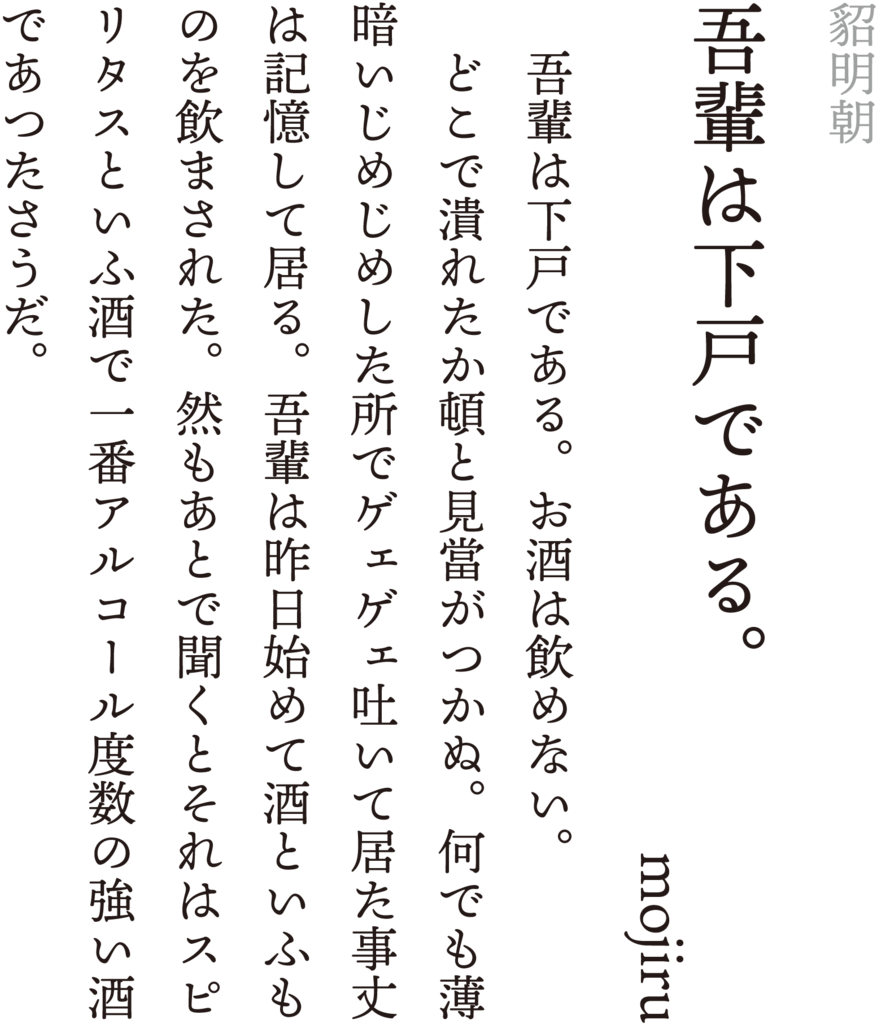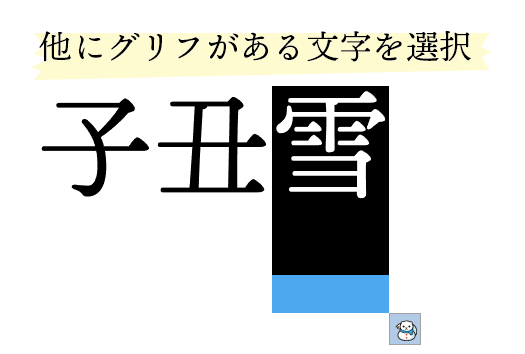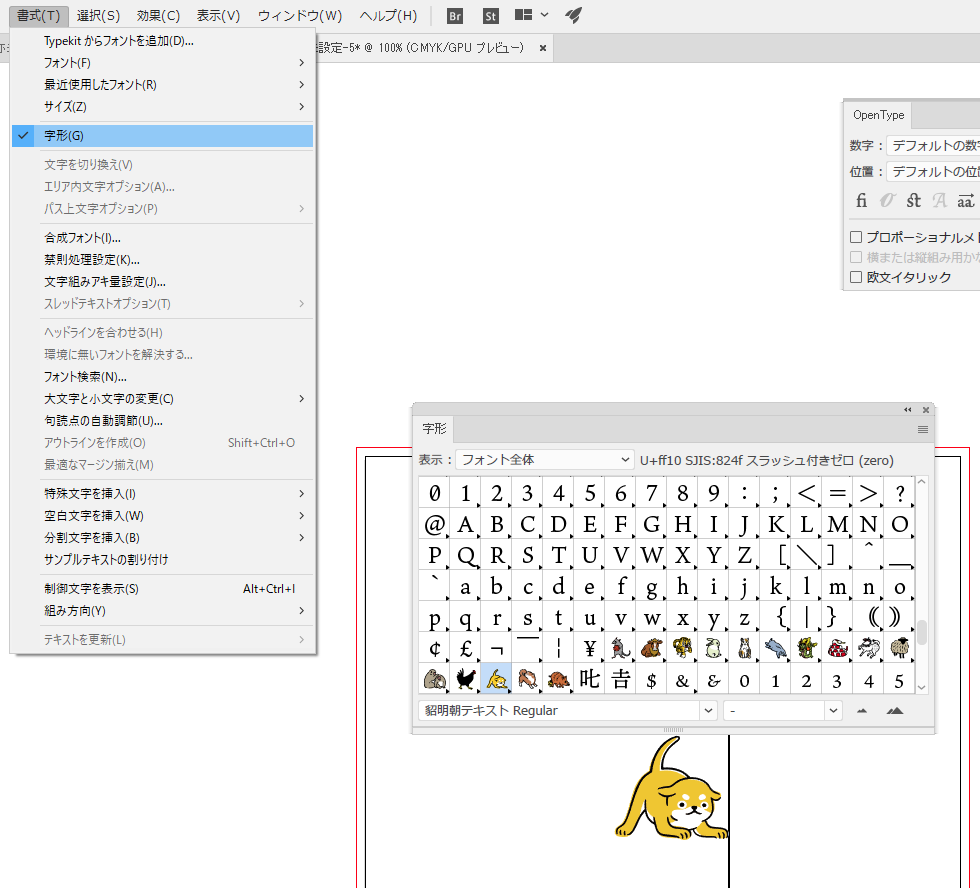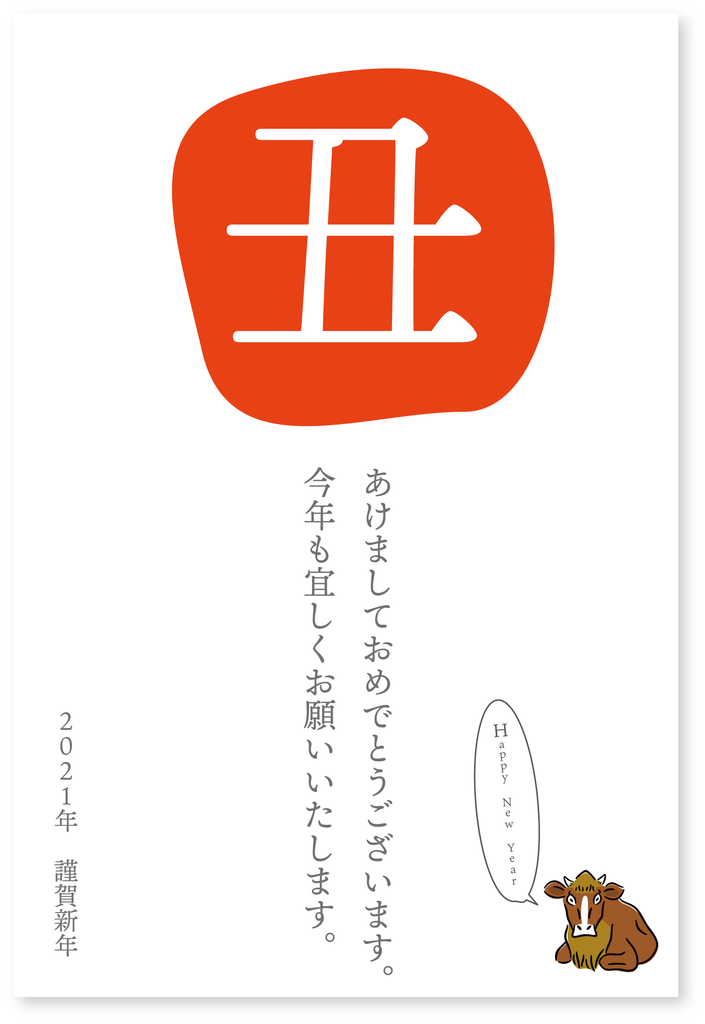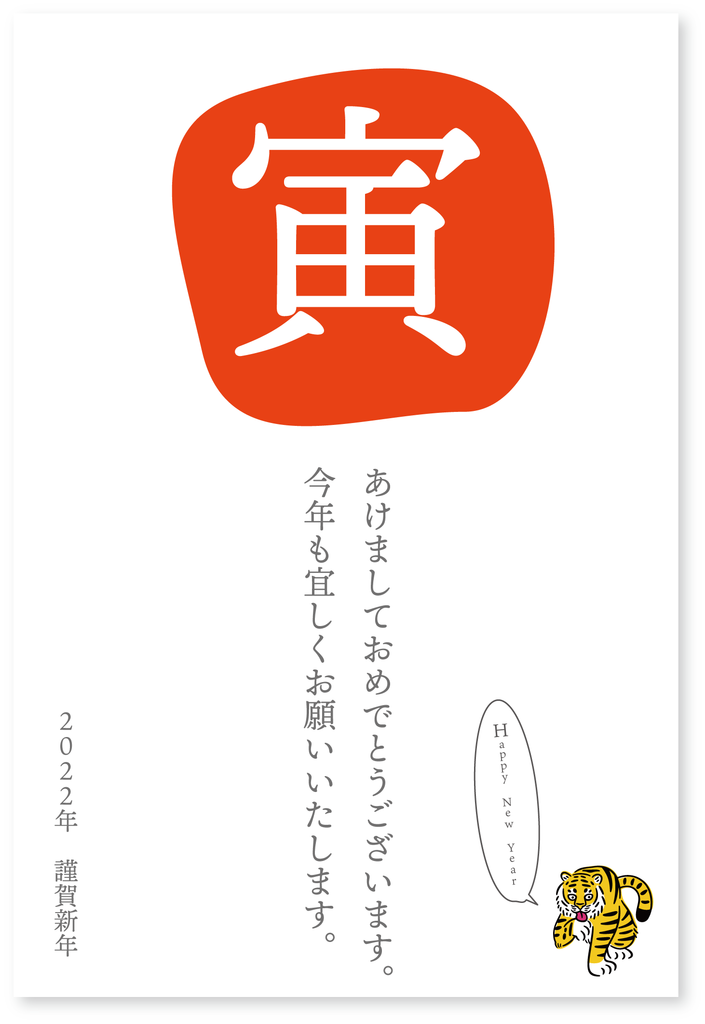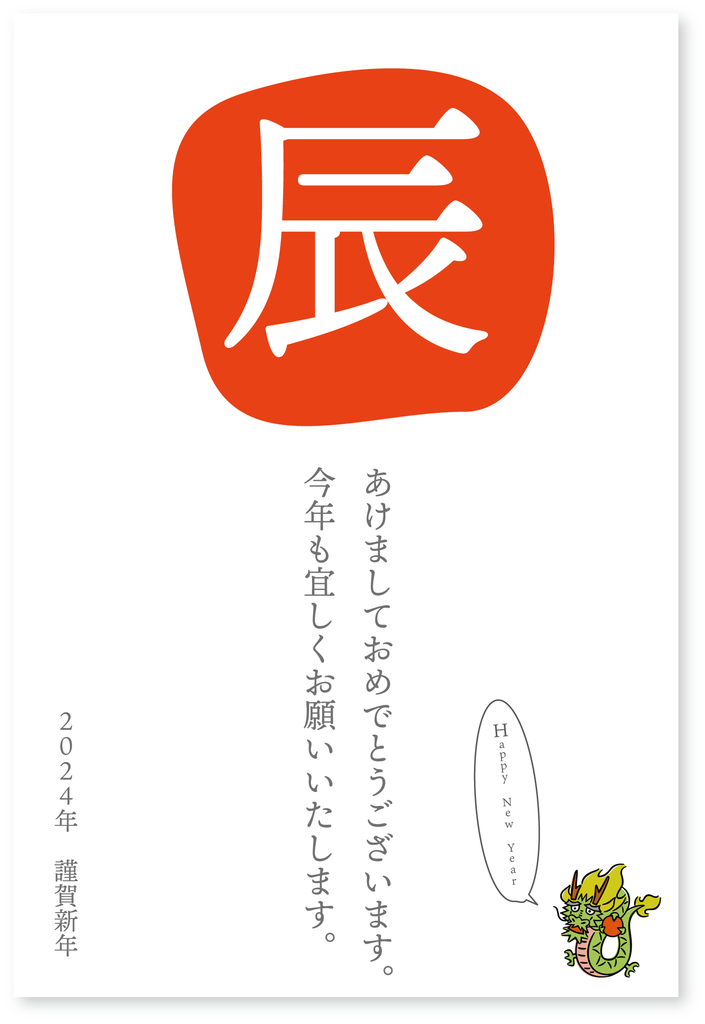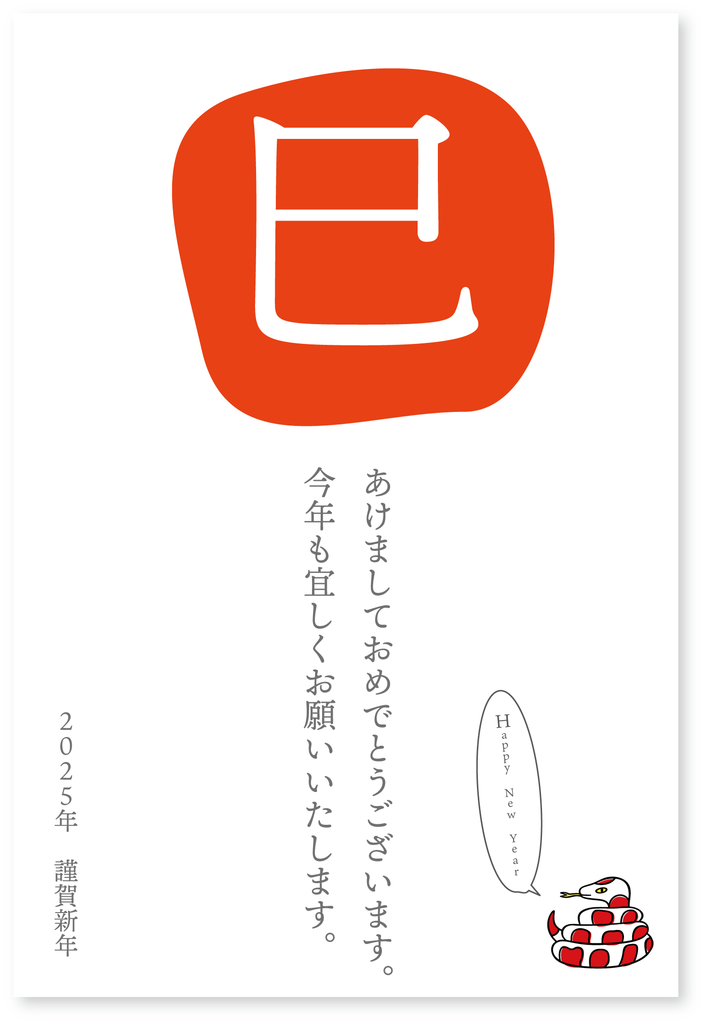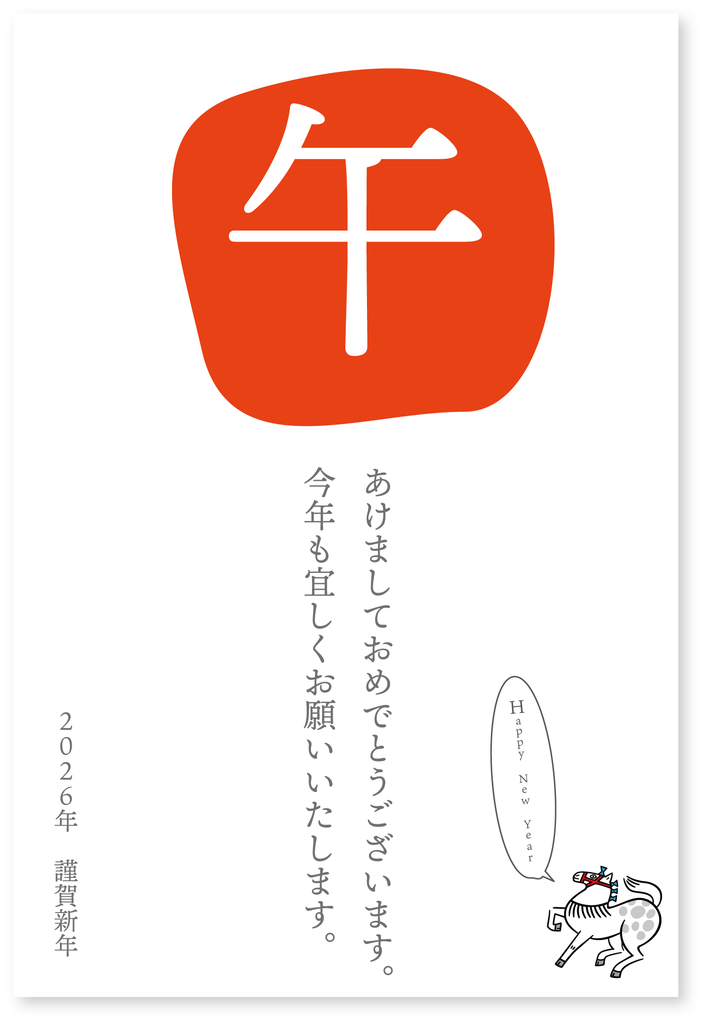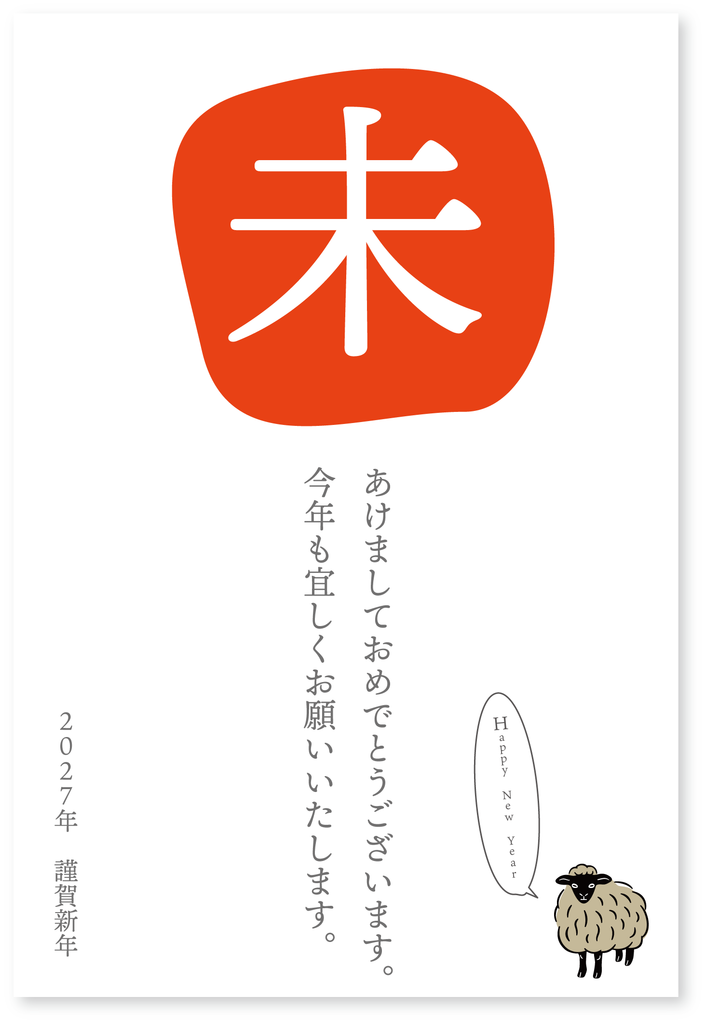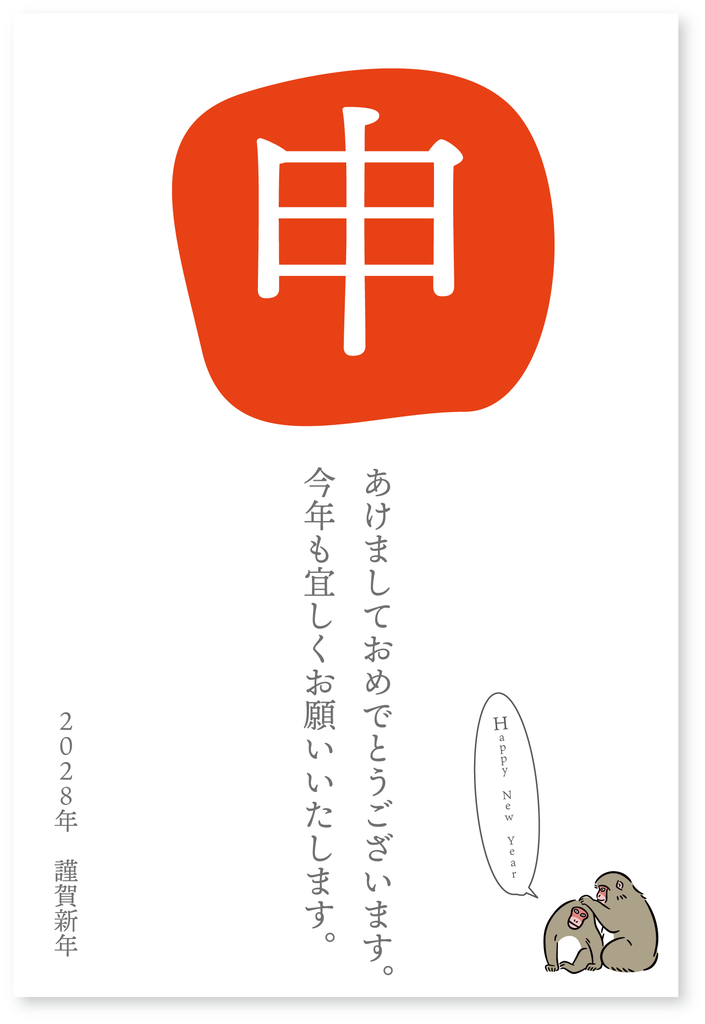
貂明朝テキスト
「貂明朝テキスト」は、貂明朝の生みの親であるアドビのチーフタイプデザイナー西塚涼子氏のデザインにより、より長文に適した仮名文字のバリエーションを搭載。
貂明朝と比べて少し抑揚を抑えてデザインされており、見出しよりも文字数の多い、本文用のテキストとして使いやすくなった。
また、西塚涼子氏のデザインによる妖しくも可愛いSVGカラーグリフ32個を加え、新たにカラー絵文字が登場。
漢字の「貂(てん)」で変換できる4匹の貂や十二支、太陽や貂の雪だるまなど、様々な色付きのSVGグリフが隠されている。LINEのスタンプとかで正式に出してくれないかな。
貂明朝テキストと貂明朝の違い
貂明朝テキストのかわいらしいSVGグリフを探そう!
AdobeR Illustratorの場合、「雪」など他にグリフのある文字を選択すると、選択肢として勝手に出てくる。
また、書式から字形ツールを選択して探す。
十二支のカラーイラストがかわいく、「年賀状」にも良さそうな貂明朝テキスト
子・丑・寅・卯・辰・巳・午・未・申・酉・戌・亥の全てのカラーイラストが文字として使えるので、年賀状はもうこのフォントを使用して作成すれば良いのではないかという気がしてきた。
ちなみに戌だけ2種類あるようだ。